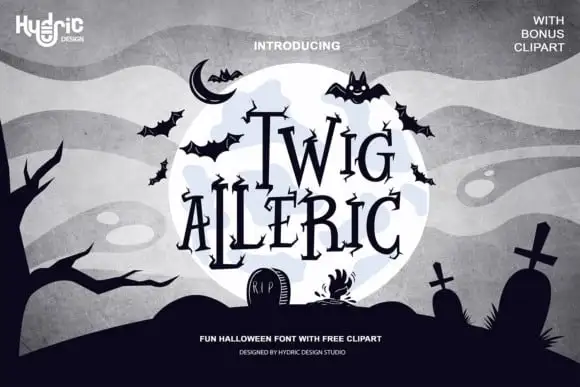
Twig Alleric Display Font – Download Grátis
A Twig Alleric Display Font é uma exuberante e desconcertante fonte gothica inspirada no feérico e místico. Ela transmite a sensação de uma árvore morta, com seus galhos desgastados e curvados sob o peso da natureza morta. Com seus traços afiados e um toque gótico que se mistura com os elementos fantásticos encontrados nas grandes produções cinematográficas, essa fonte captura a atmosfera sombria dos filmes de fantasia. O designer HydricDesign criou uma fonte única e distintiva, onde cada caractere parece um galho distorcido em movimento. Algumas das letras têm detalhes curvos que se desenrolam como as folhas dançando sob a luz tênue do fim da noite, enquanto outras seguem linhas retas e firmes como os troncos resistentes de uma árvore morta. A Twig Alleric Display Font é perfeita para aqueles projetos que buscam expressar um tom sinistro e misterioso. Seja você designer gráfico, profissional de marketing ou qualquer criativo em busca de uma fonte única e impressionante, essa opção pode oferecer a atmosfera ideal para destacar seu projeto.